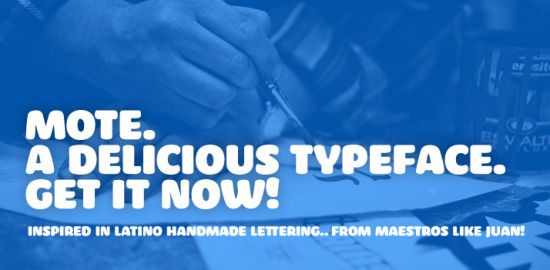
Die Bello SC ist ähnlich, aber lebendiger – ich denke ich bleibe bei der (schreib ich hier mal als Ausrede hin, um auch diese neue Rubrik unauffällig zu loben).